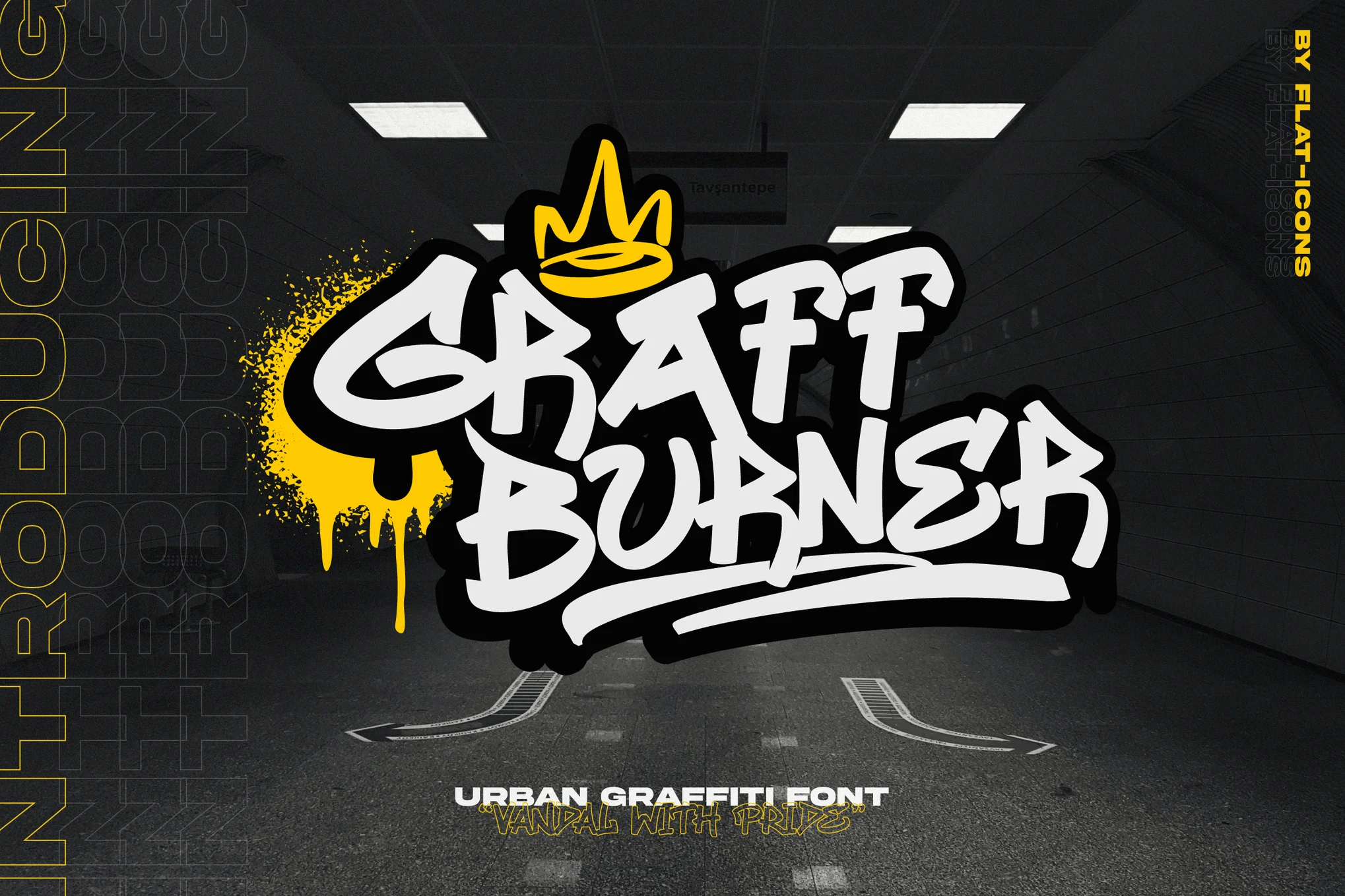
آیا می خواهید کمی روح شهری را به طراحی خود اضافه کنید؟ به دنبال فونتی هستید که تاثیرگذار باشد؟
معرفی Graff Burner – یک فونت Urban Graffiti.
با فونتی که فرهنگ شهری را درک می کند، طرح خود را به هنر خیابانی واقعی تبدیل کنید. چاپ یا دیجیتال، Graff Burner توجه مخاطبان شما را جلب خواهد کرد. آن را امتحان کنید و رشد برند خود را ببینید.
پشتیبانی چند زبانه و لیگچر
مجموعه کامل علائم نگارشی و اعداد